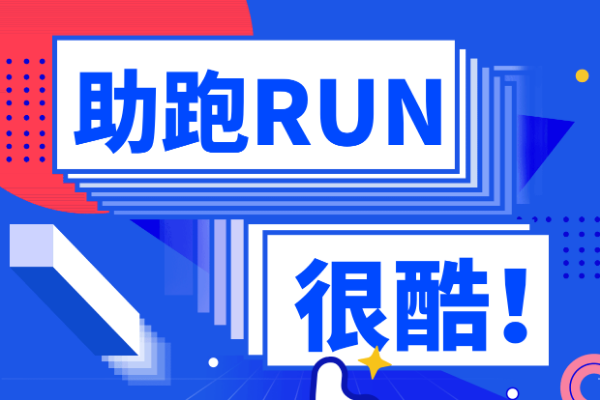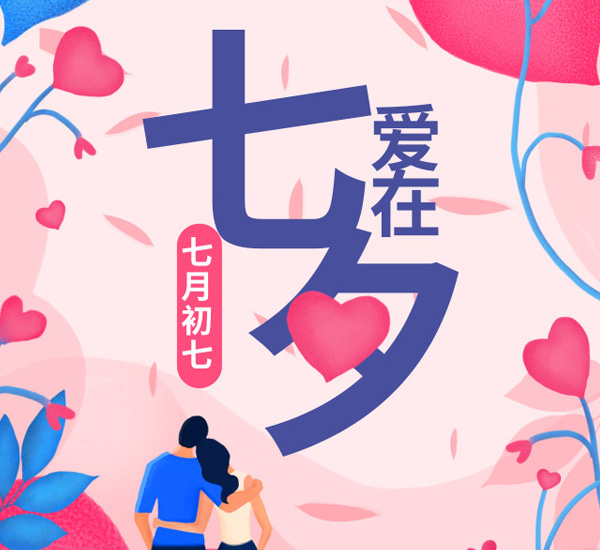
思源黑体-简体中文版
思源黑体是由Adobe和谷歌共同开发和推广的一种开源字体。从2014年开始,经过持续的修正和完善,其在全球范围内产生了深远影响。思源柔黑、思源真黑等字体均是在这个开源平台基础上衍生出来的。这些字体具有很高的实用性,不仅支持日文、韩文、繁体中文和简体中文,还包含来自Source Sans字体家族的拉丁文、希腊文和西里尔文字形,每种都有65536个字形。
Google将这种字体命名为Noto SansCJK,作为Google的Noto字体家族的一员。而Adobe则将其命名为Source Han Sans,作为Adobe的Source字体家族的一员。需要注意的是,Adobe拥有这些字体的设计版权,发布的字体文件可以无限制地免费使用。
总的来说,思源黑体是一种功能强大的开源字体,具有很高的实用性和广泛的适用范围。无论是用于印刷媒体还是电子设备,它都能呈现出出色的视觉效果,满足各种排版需求。